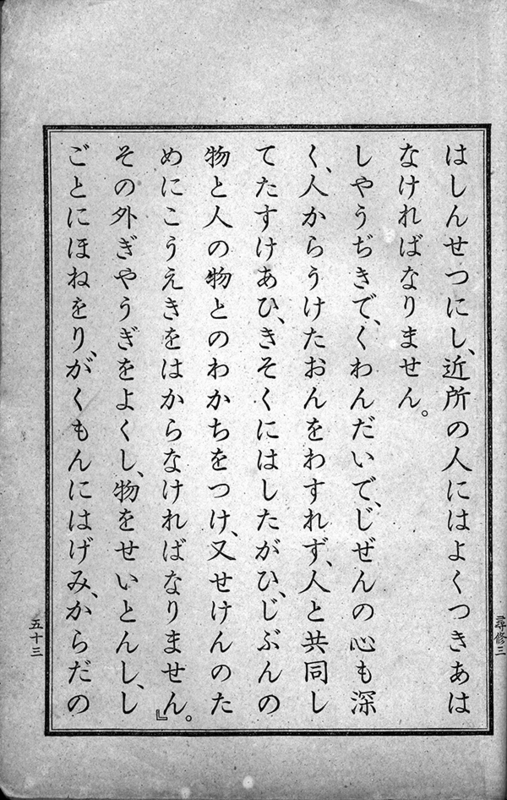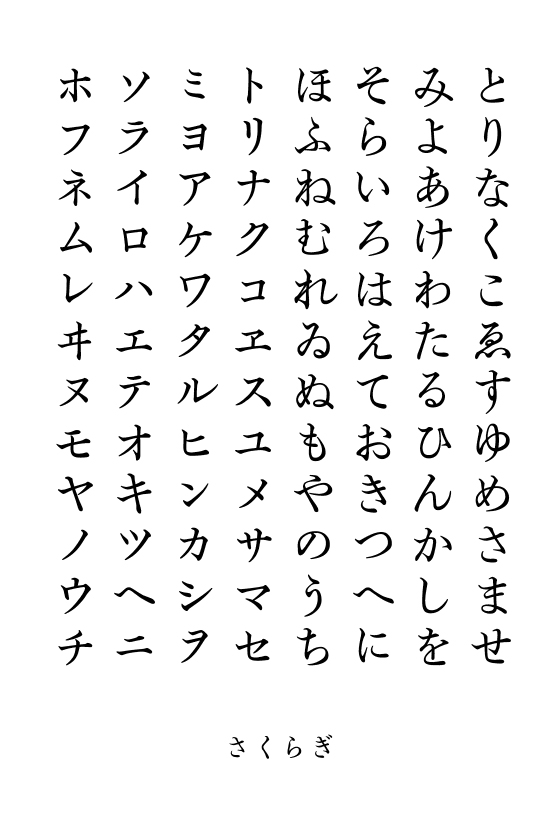
05-3 和字書体「さくらぎ」のよりどころ
原資料:『尋常小学修身書巻三』(東京書籍、1919年)
『尋常小學修身書 巻三』は、翻刻発行兼印刷者・東京書籍株式会社、発売所・株式会社国定教科書共同販売所となっている。「修身」の教科書で、二宮金次郎、本居宣長、上杉鷹山、徳川光圀、貝原益軒らが登場している。
1903年(明治36年)に小学校令が改正され、小学校の教科書は国定教科書となった。さらに、1909年(明治42年)には、日本書籍・東京書籍・大阪書籍の三社が翻刻発行をして、国定教科書共同販売所が販売することになった。
教科書に金属活字が一般的に採用されるようになるのは、他の書物にくらべて遅れていた。1933年(昭和8年)までは、おおむね木版印刷によるものが多かった。
活字書体「さくらぎM」